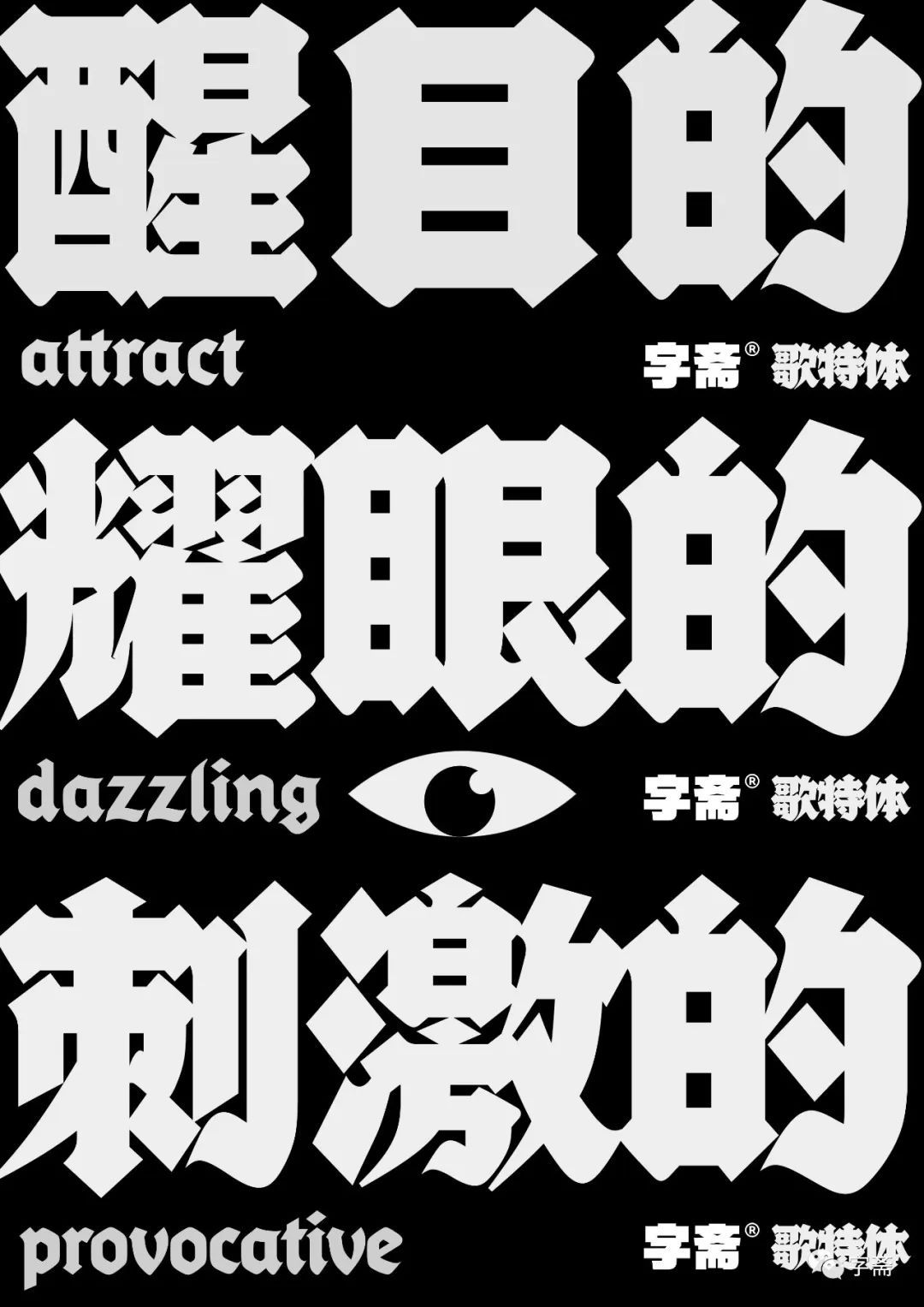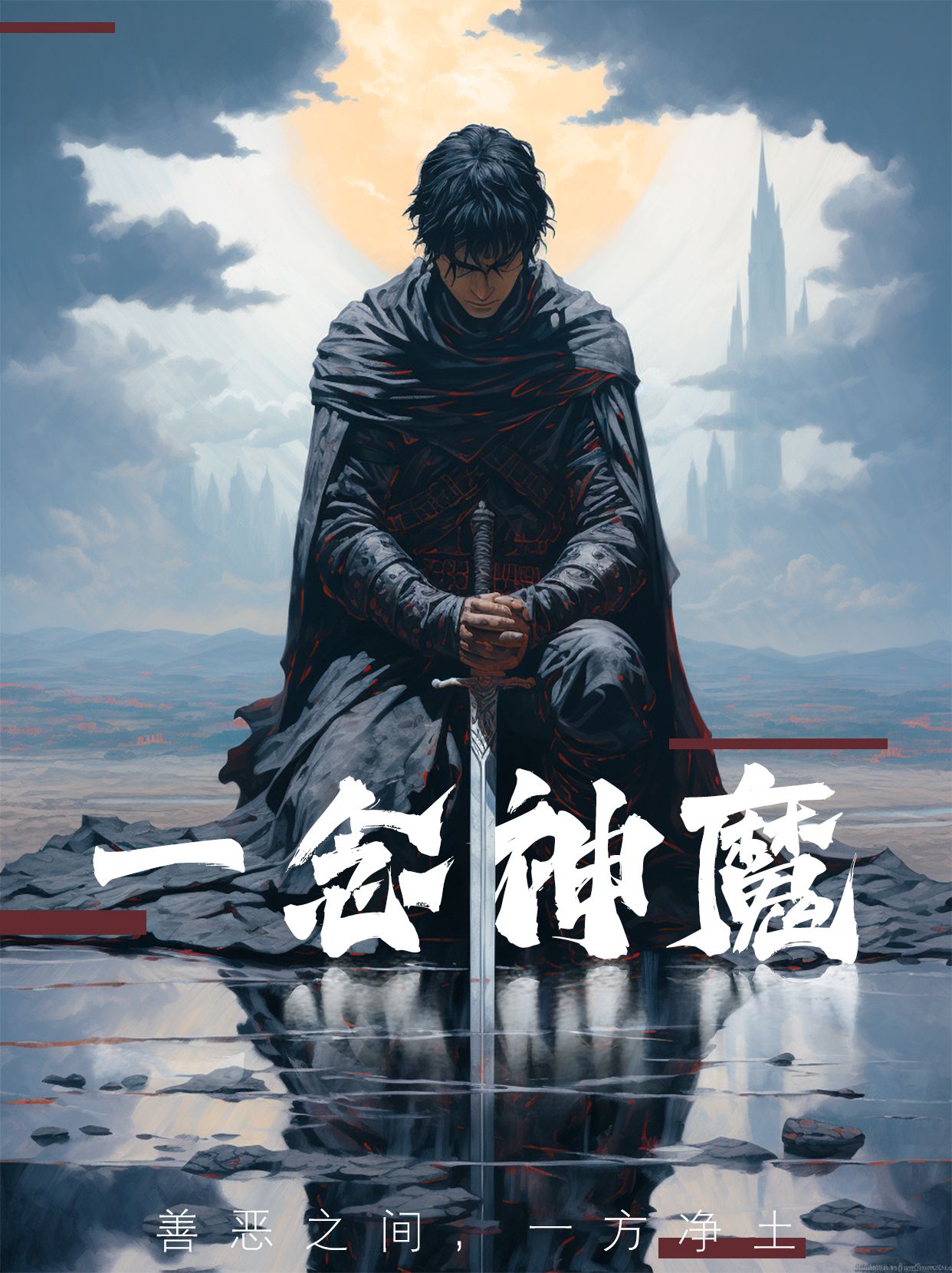
游戏世界中的视觉盛宴:四款绝佳游戏字体推荐
在虚拟的游戏世界中,文字不仅是信息的载体,更是氛围营造的重要元素。一款合适的字体,能够瞬间提升游戏的视觉表现力,让玩家沉浸其中。今天,就为大家推荐四款专为游戏设计的字体,它们各具特色,定能为你的游戏世界增添无限魅力。
这款现代创意型黑体,以其独特的风格在游戏界独树一帜。字型厚重而不失灵动,笔画粗细不均,横竖笔画梯形分布,打破了传统黑体的呆板印象。撇、捺、点的梯形元素加入,让整体风格更加硬朗,不规则感的设计更是赋予了它强烈的现代文艺气息。无论是用于游戏标题还是界面文字,都能瞬间抓住玩家的眼球。
这款书法字体字形稳重,笔画张扬,仿佛豪侠仗剑江湖,尽显潇洒之风。折、提、钩等部首干净利落,高度折叠,让人联想到武侠世界中的刀光剑影。在游戏角色介绍、剧情描述等场景中,这款字体能够完美诠释游戏的武侠氛围,让玩家仿佛置身于刀光剑影的江湖之中。
笔墨浓厚,粗细对比鲜明,这款字体结构中正,笔画特点夸张,极具视觉冲击力。特别是“勾、提、挑、捺”等笔画的处理,更是将字体的张力展现得淋漓尽致。在游戏中的战斗场景、BOSS介绍等需要强调力量感的环节,这款字体无疑是一个绝佳的选择。
哥特体以其独特的尖顶造型和优雅线条,深受游戏设计者的喜爱。高手字斋哥特体Pro更是将这一风格发挥到了极致。无论是用于游戏界面的装饰性文字,还是作为游戏内的重要提示信息,这款字体都能以其独特的韵味,为游戏增添一份神秘与优雅。
以上四款字体,各具特色,无论你的游戏风格是现代、武侠还是奇幻,都能在其中找到最适合的那一款。快来为你的游戏世界选择合适的字体吧!